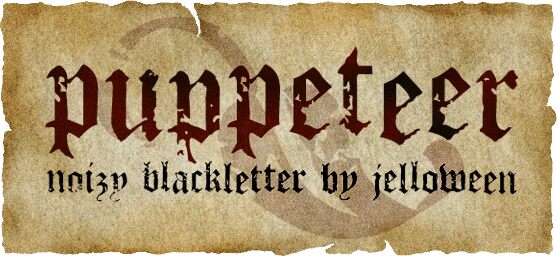
Puppeteer (autor: Tjarda Koster) to darmowy, erodowany krój gotycki o gęstych średniowiecznych formach i ostro ciętych pociągnięciach. Jego wyszczerbione powierzchnie sprawiają, że formalne kształty wyglądają na poszarpane i stare.
Może pełnić rolę zniszczonego, teatralnego tytułu na plakatach horrorów, w grafikach gier dark fantasy i materiałach na imprezy halloweenowe, gdzie poszarpane kontury i złamane pociągnięcia sprawiają wrażenie, jakby należały do wyimaginowanego świata, a nie go ozdabiały. W przypadku gadżetów muzycznych metalowych i opakowań napojów specjalnych, ten sam zużyty krój gotycki może ukształtować ponurą, staroświecką tożsamość marki, a litery działają niemal jak pęknięte godło lub rzeźbiony szyld sklepowy.